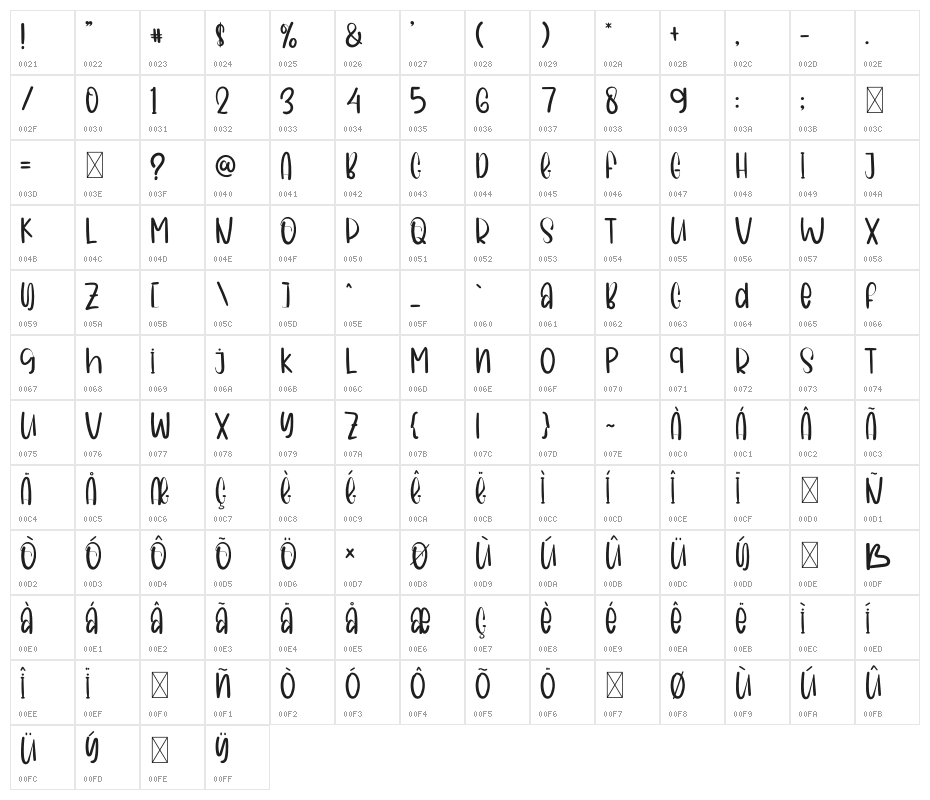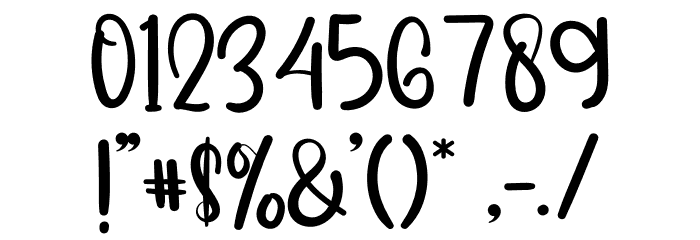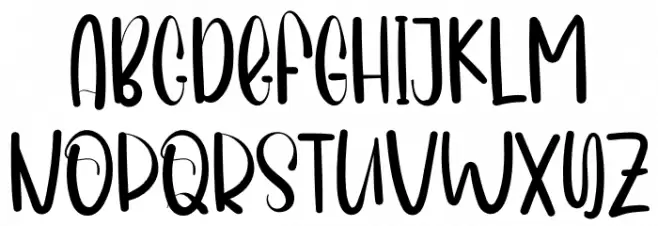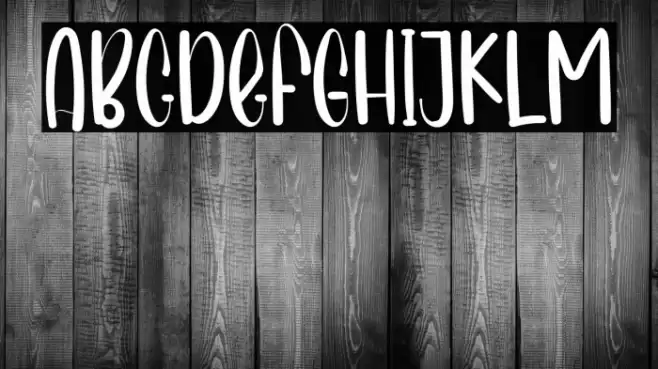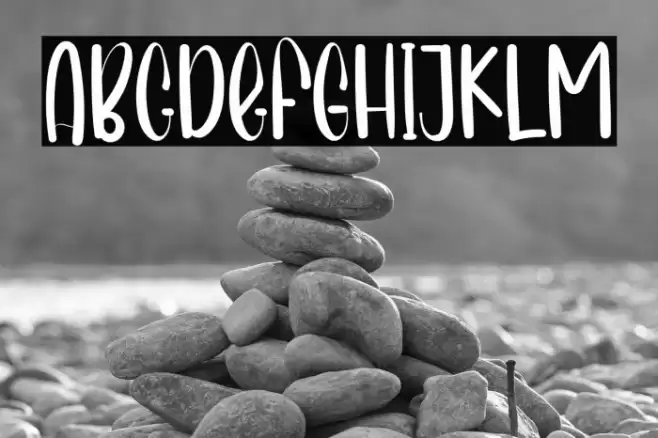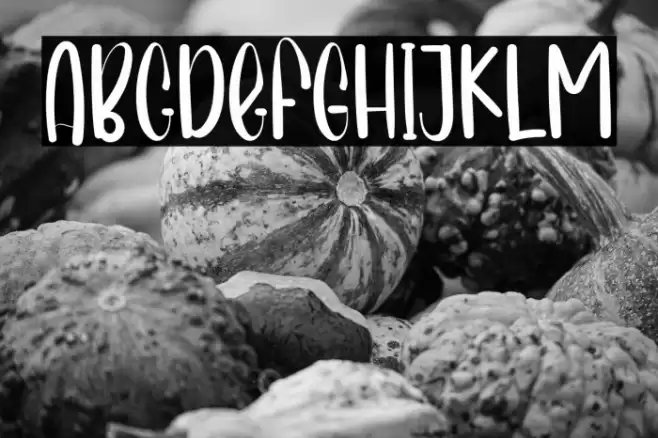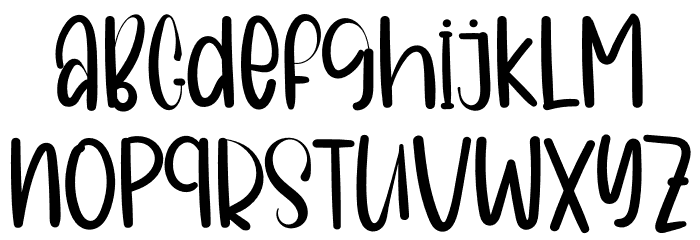
Sunshine In Winter Font
| Catégories | Cartoon |
| Style général | Playful, Whimsical |
| Projets proposés | Ideal for children's books, greeting cards, playful branding, and creative posters. |